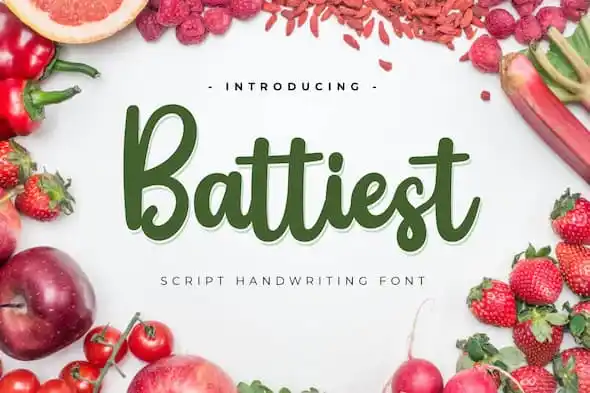
Battiest Script Font – Fonte Grátis
Battiest Script Font
A Battiest Script Font é uma nova descoberta no mundo das fuentes escrita à mão, especialmente projetada para oferecer uma experiência de escrita agradável e encantadora. Suas curvas fortes dão à fonte um toque moderno que torna-a ainda mais bela e elegante em qualquer uso. Além disso, sua personalidade única é imediatamente perceptível quando você começa a explorá-la. Seja para criar cartões de convite sofisticados ou obras de arte digitais memoráveis, esta fonte escrita à mão oferece um toque autêntico que se destaca. Convidamos você a descobrir o encanto da Battiest Script Font, uma verdadeira jóia em nossa gama de fuentes escrita à mão.